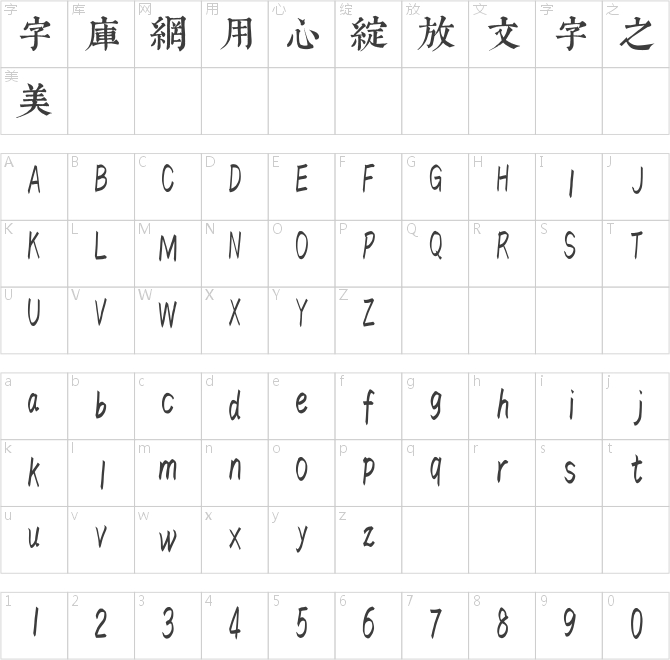
字體名稱: 漢標康熙字典內
漢標康熙字典內府繁
作品的主要特征:字體版刻清晰,行格疏朗,古樸清新,雕刻刀法精湛;
作品的主要特點:最大化的保留古籍刻本字體原貌,對印制不清的字體進行了修復還原,字體邊界清晰,線條流暢,大小均等。
選用清康熙五十五年(1716)武英殿刻本,又稱內府刻本,康熙內府刻本多用于內廷賞賜之用,民間流傳較少。該刻本為初印本,初刻初印,字典墨色濃郁,字跡秀美、雕刻刀法精湛、將原書以600dpi進行掃描并進行摳字,將原書中的文字分別提取出來,進行一些修繕后轉 成矢量輪廓,并非如一般字體設計那樣手動繪制矢量曲線。對一些字進行了拼版,保證了古籍印刷的美觀和實用性。
漢標康熙字典內府繁字體字庫是一款讓人賞心悅目、百看不厭的中文字體,適合各類廣告和產品包裝設計應用,字體大小7.25MB,格式為ttf字體,上傳用戶是漢標文創,作者/版權方為漢標字庫